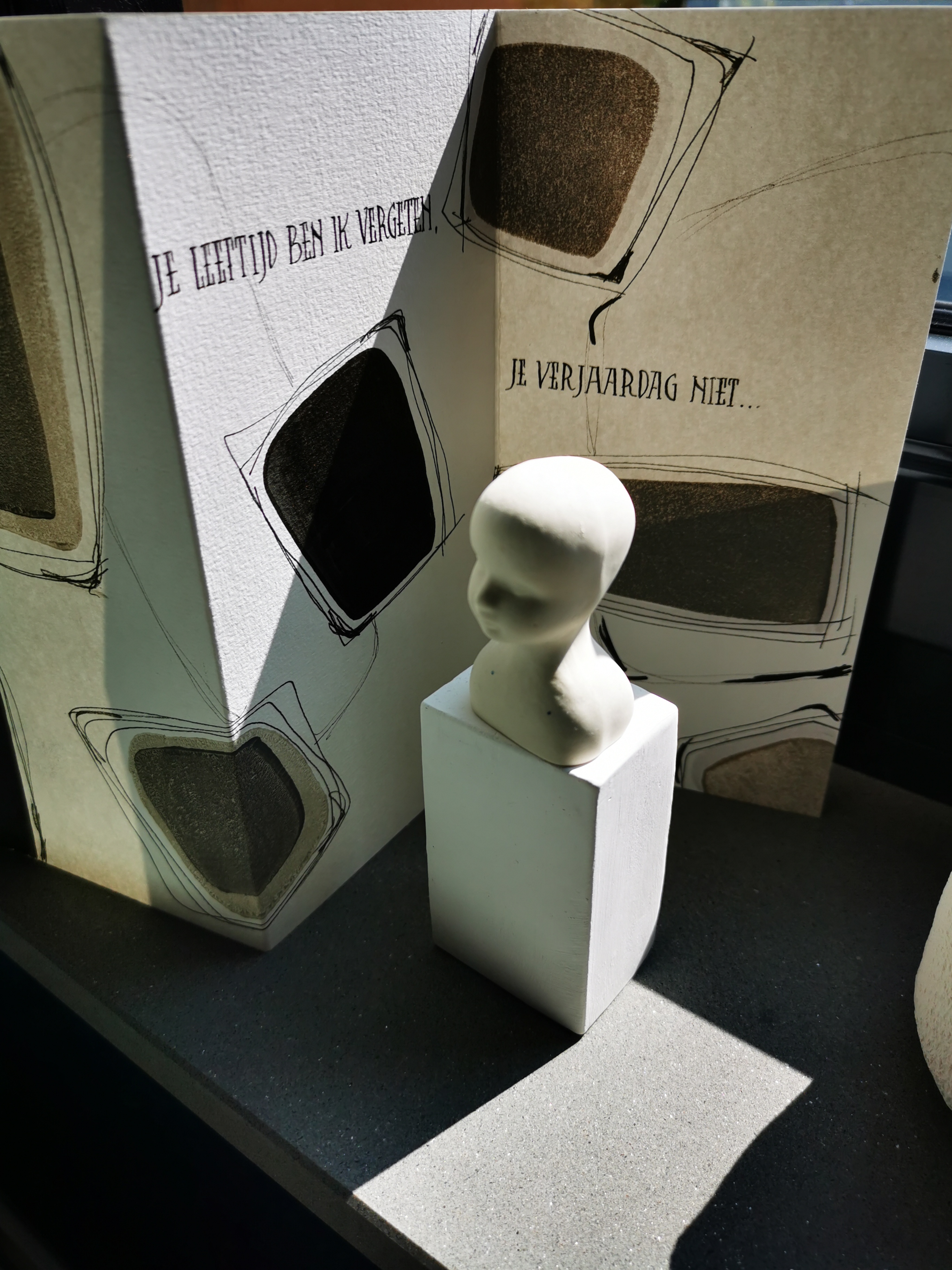
Deze maakte ik om mijn voorraadje terug aan te vullen:
2 birthday cardsfor my stash:
| zwarte fineliner - aquarelverf / black fineliner with colour splashes of watercolour |
Het was de 75ste verjaardag van mijn moeder vorige donderdag. Blauw is haar lievelingskleur, dus schilderde ik deze aquarelbloemen voor haar met een gepaste tekst in potlood.
Last Thursday was my Mum's 75 th birthday. Her favourite colour is blue, so I painted these watercolour flowers for her and an appropriate text in pencil.
| de cover is van een leer-achtig soort papier - leather-like paper for the cover |
Uit een aantal oefenbladen maakte ik deze doosjes, in verschillende maten en hoogtes. Altijd handig om op voorraad te hebben .
From some practice sheets I made these 4 boxes, in different sizes and heights. Always handy to have in stock .Nothing special, just some basic boxes.
| bovenkant - top |
| onderkant - bottom |
Ook maakte ik ong 30 mini-doosjes als probeersel om samen in een compositie op te plakken.
I also made about 30 baby boxes attempting a nice composition, gluing them all together.
| op een karton samengelegd op zoek naar een goeie compositie-piecing them together looking for a pleasing composition. |
I found a previous project I wasn't really happy with, so I glued some tea bags on top. Then I glued the baby boxes down and cut out letters from old magazines. Together it reads 'thinking outside the box'.
Made this triptych card using foam print with acrylic paint.
Vorige week zijn we weer met de nieuwe lessen gestart: het lusjesalfabet.
Hieronder vind je mijn eerste probeersels:
Last week we started the new calligraphy lessons; an alphabet with a lot of loops, as you can see in my first exercises: